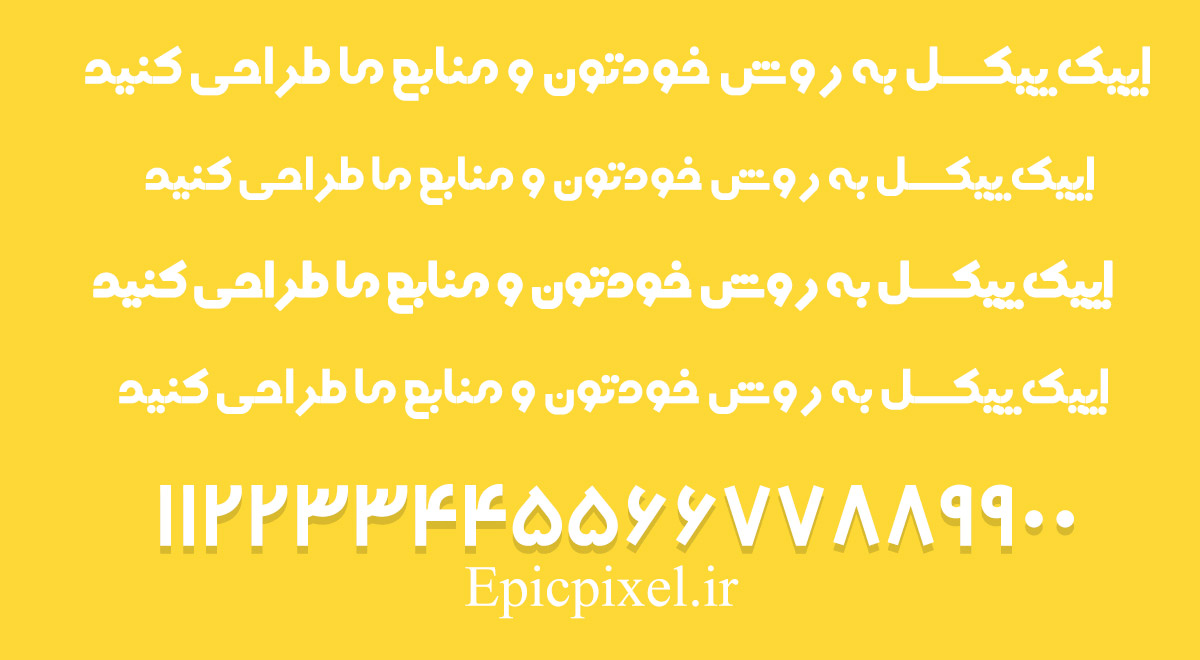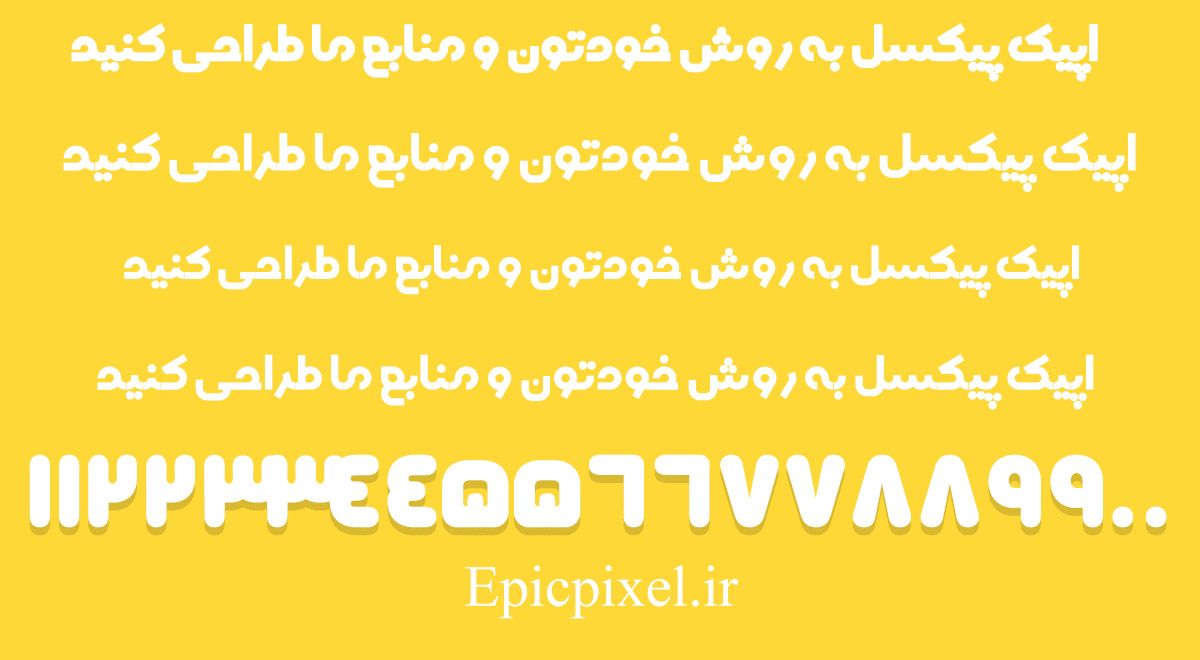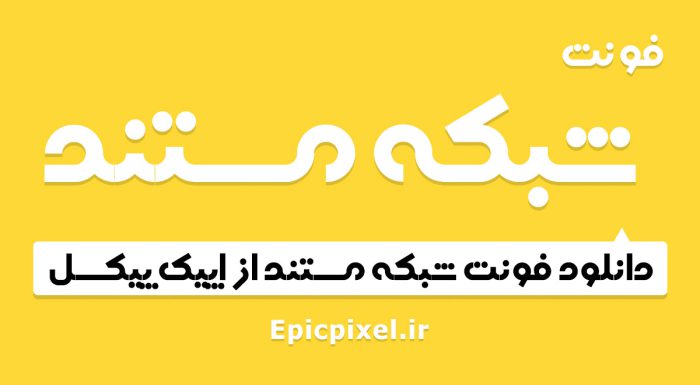
2 فونت شبکه مستند فارسی
دانلود مجموعه کامل فونت Mostanad فارسی Font مستند رایگان |
البته واقعا شبیهه ولی نکته اش اینجاست که خیلی نزدیک هستند بیش از نود درصد شبیه هم هستند ولی شبکه مستند نقطه هایش تو یه خط هست ولی تو این فونت نقطه های ن با ت تو یه خط نیست